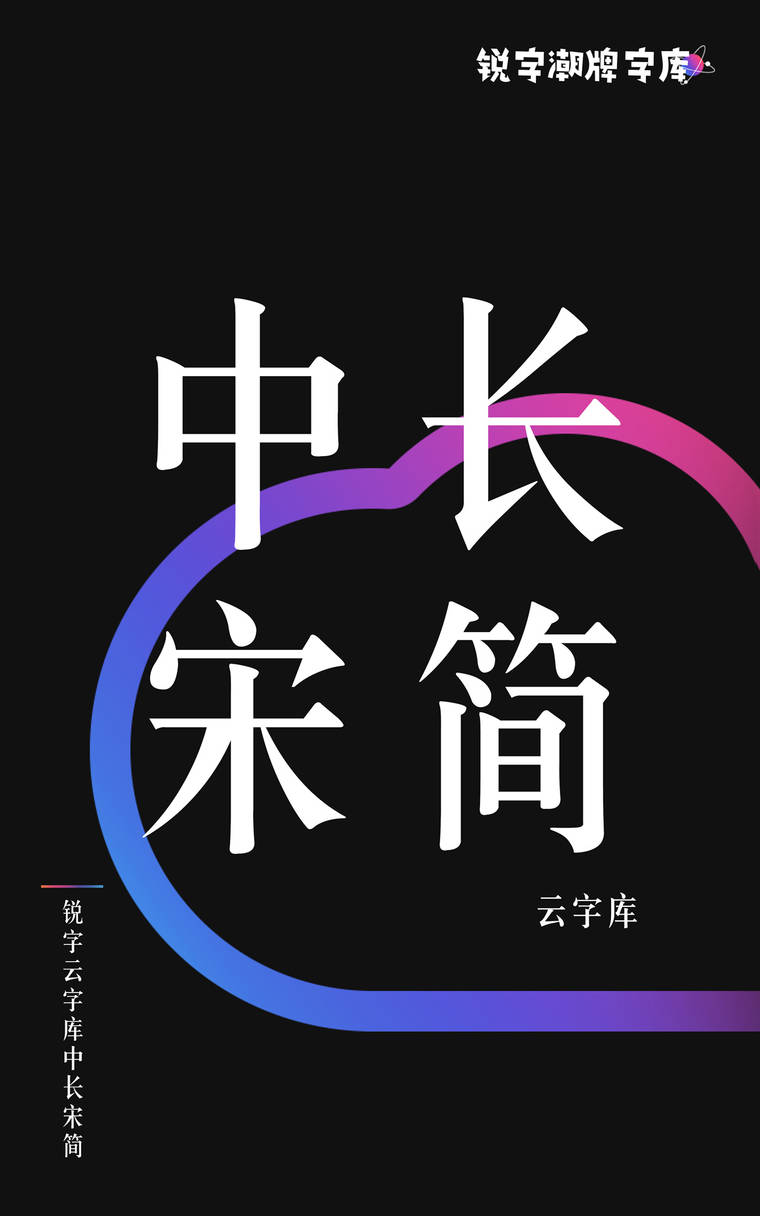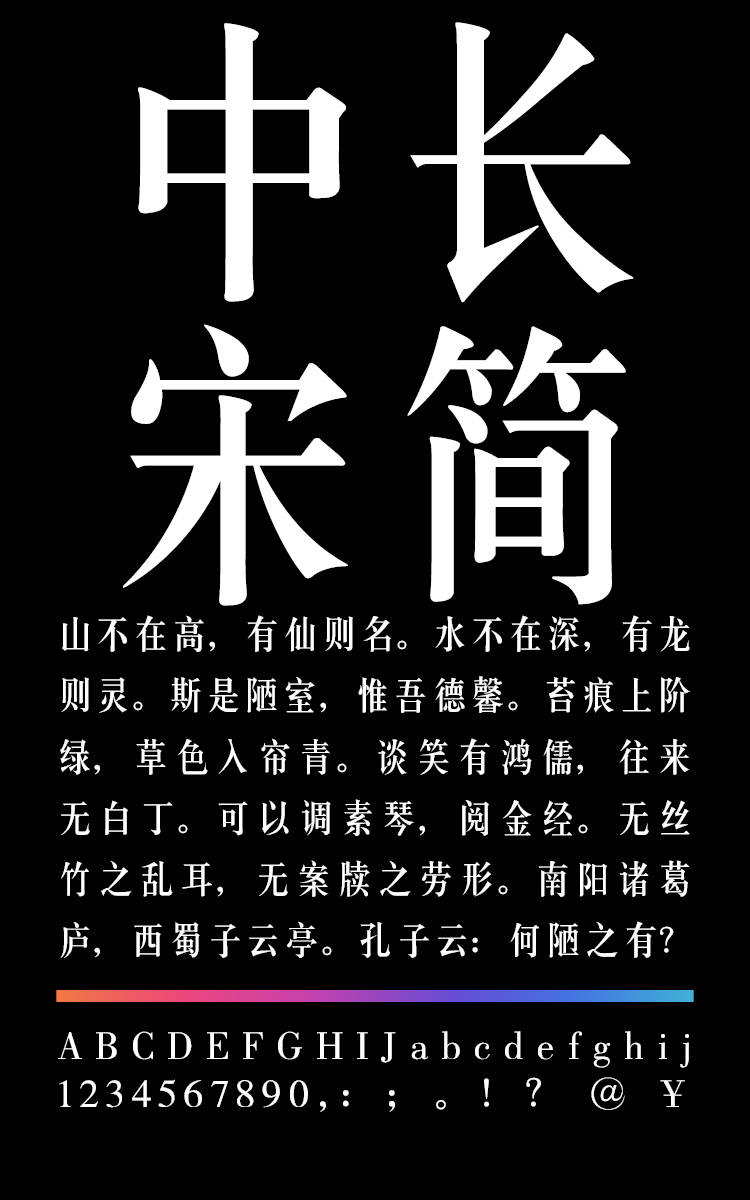
锐字云字库中长宋简
锐字云字库中长宋简,这款字体结构工整、笔画清晰,兼顾美观与易读性,适用于标题、正文、海报、包装、LOGO 等多种场景。字形优雅稳定,风格百搭耐看,适配日常排版与创意设计,让文字呈现更舒适、更具质感。锐字云字库中长宋简一笔一画,皆是细节,以均衡的比例、流畅的线条打造舒适视觉体验,字形端正大气,风格简约现代。无论是商业设计、品牌宣传还是日常排版,都能轻松驾驭,让文字更有格调与力量。锐字云字库中长宋简字体下载。
字体特征:字形清秀、古朴,与宋体特点相似,但字身长,风格典雅、工整、严肃、大方,字体清秀,横轻竖重,结构均匀,笔法严谨,美观实用。